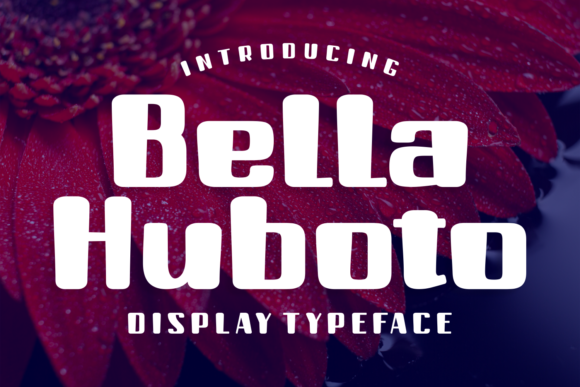
Bella Huboto
Encontrar los elementos de diseño adecuados puede ser un desafío, pero Bella Huboto ofrece una colección excepcional que eleva tu trabajo al instante.
Elaborado con precisión, Bella Huboto proporciona vectores limpios, tipografía suave y una licencia comercial para tu tranquilidad.